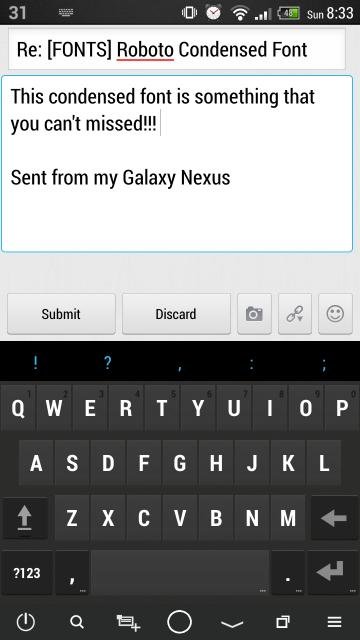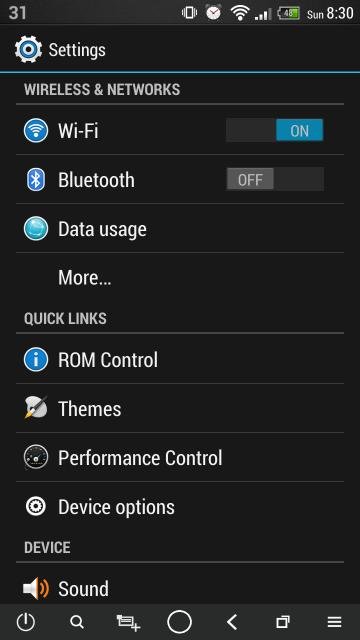
[FONTS] The Amazing Roboto Condensed Font - Android 4.3 !!! [1 July 2013]
Also ist das der möglichst genau Abklatsch der Schrift die man auf Leak-Bildern erkennt die angeblich von Google stammen und auf der Uhr 4:30 haben?
Hätte wohl den Artikel lesen müssen, die Fonts wurde von einer Firmware 4.3 Leak entnommen.
Nachtrag: Offenbar ist die Fonts für alle Handys.
Oha , sehr gewöhnungsbedürftig...
Du weisst aber dass du die Robot-Regular Schriftart nehmen um dein annähernd gleiche Ergebnis zu bekommen wir vorher?
Ist das nicht eher die Font von Samsung? Sieht mir nicht nach einer Nexus Font aus.
Die Schriftart ist auch nicht nur für das Nexus, es ist schlicht und einfach die Vanilla-Art. Das Build kommt aber vom Samsung Galaxy S4.
Die Schriftart oben im Screenshot sieht ja schrecklich aus! oO Oder wirkt das nur anders? In meinen Augen irgendwie lang gezogen.
//EDIT: Ich hab's nochmal verglichen. Aber seht selbst:
Ach du scheiße. Man kann sich zwar an vieles gewöhnen aber nicht an die schlechte Lesbarkeit.
Amazing? Den hab ich schon seit der Font in Sense 5 verwendet wird.